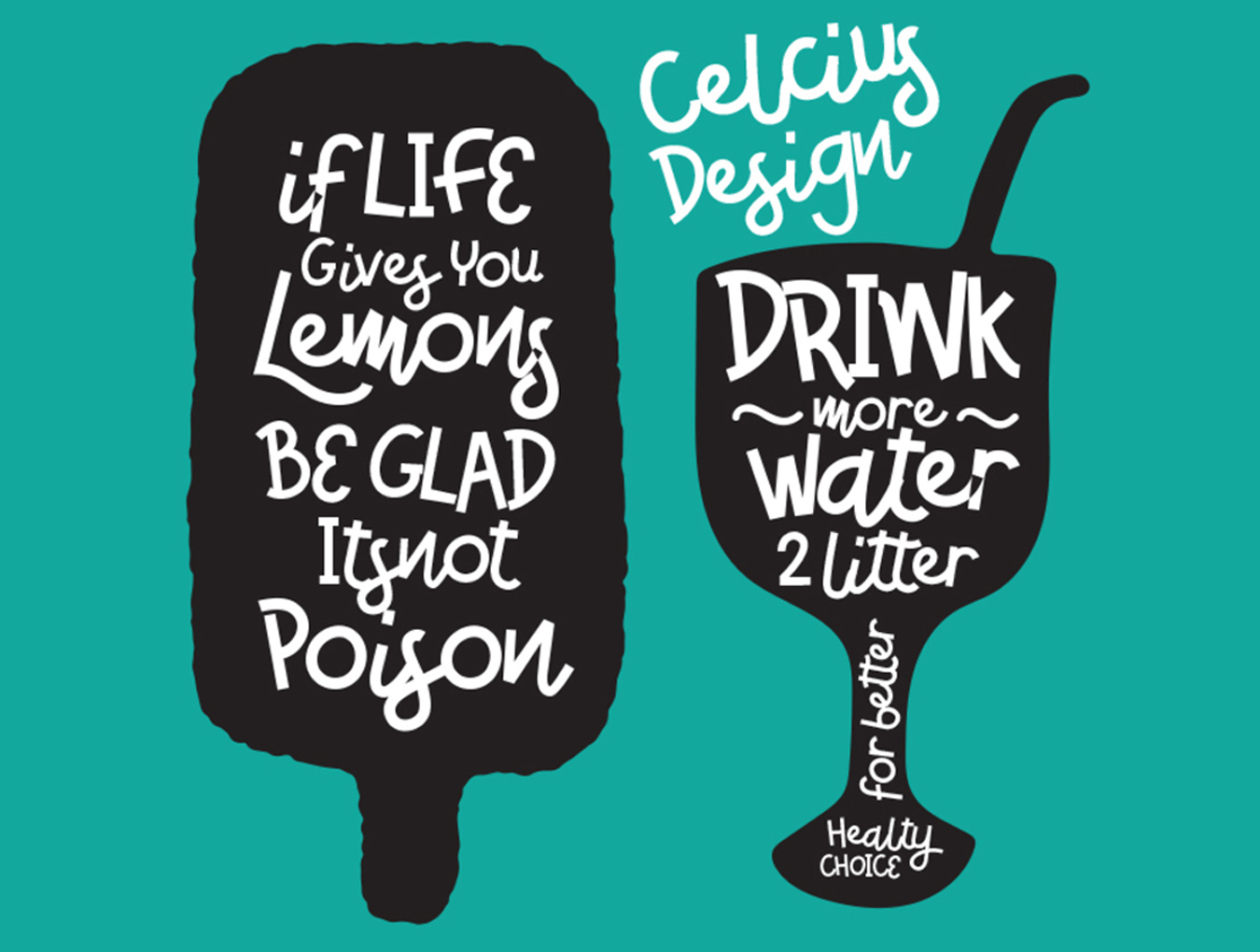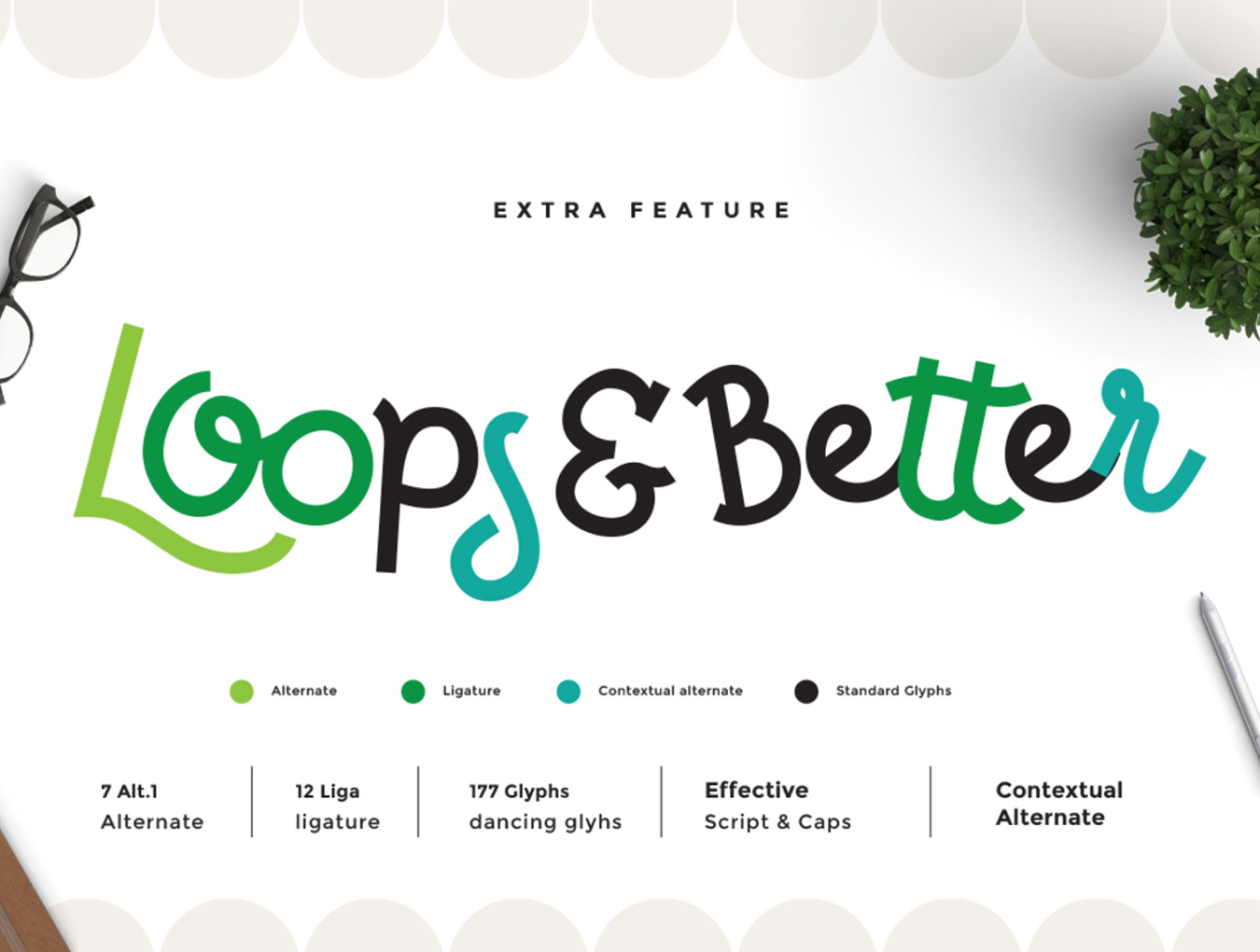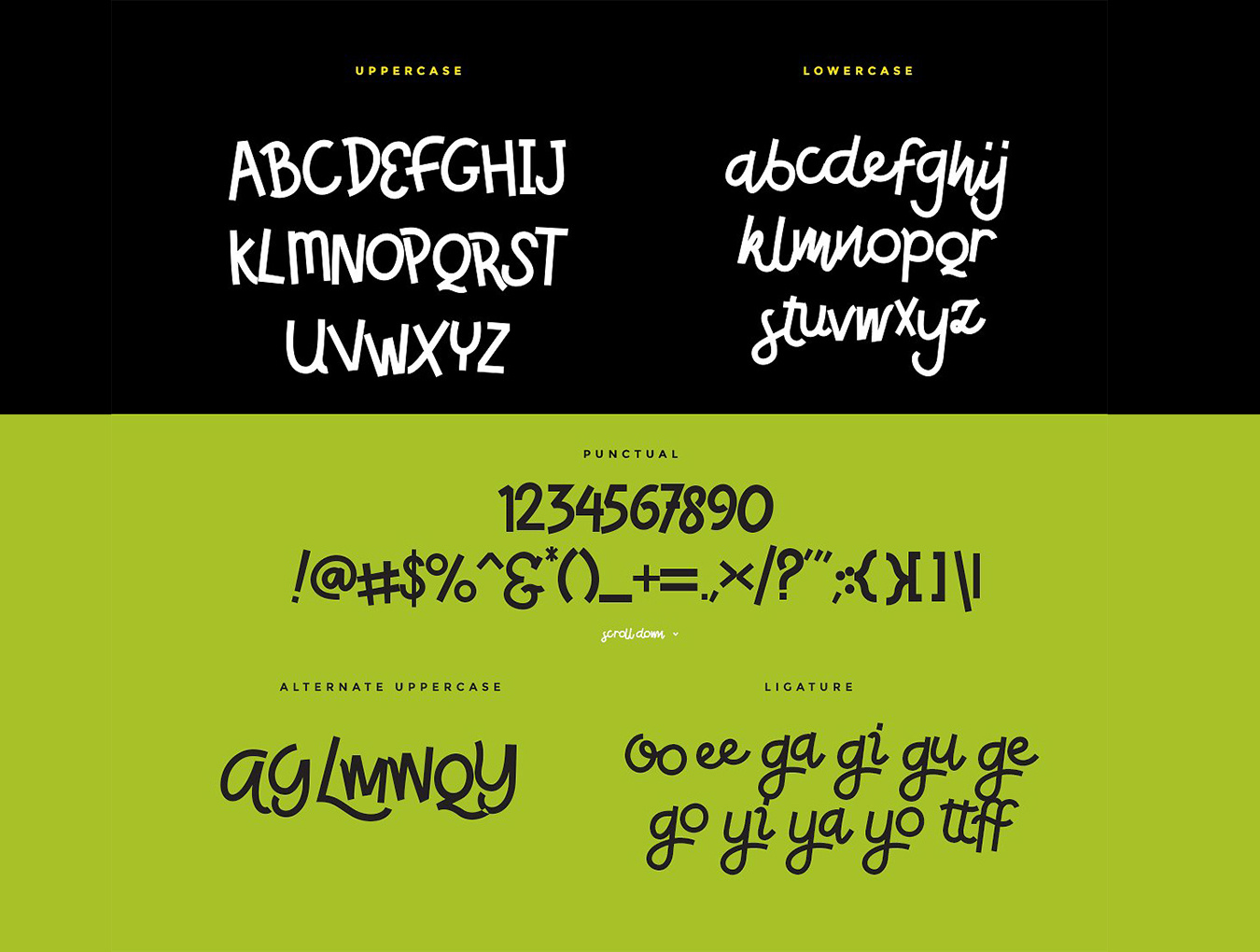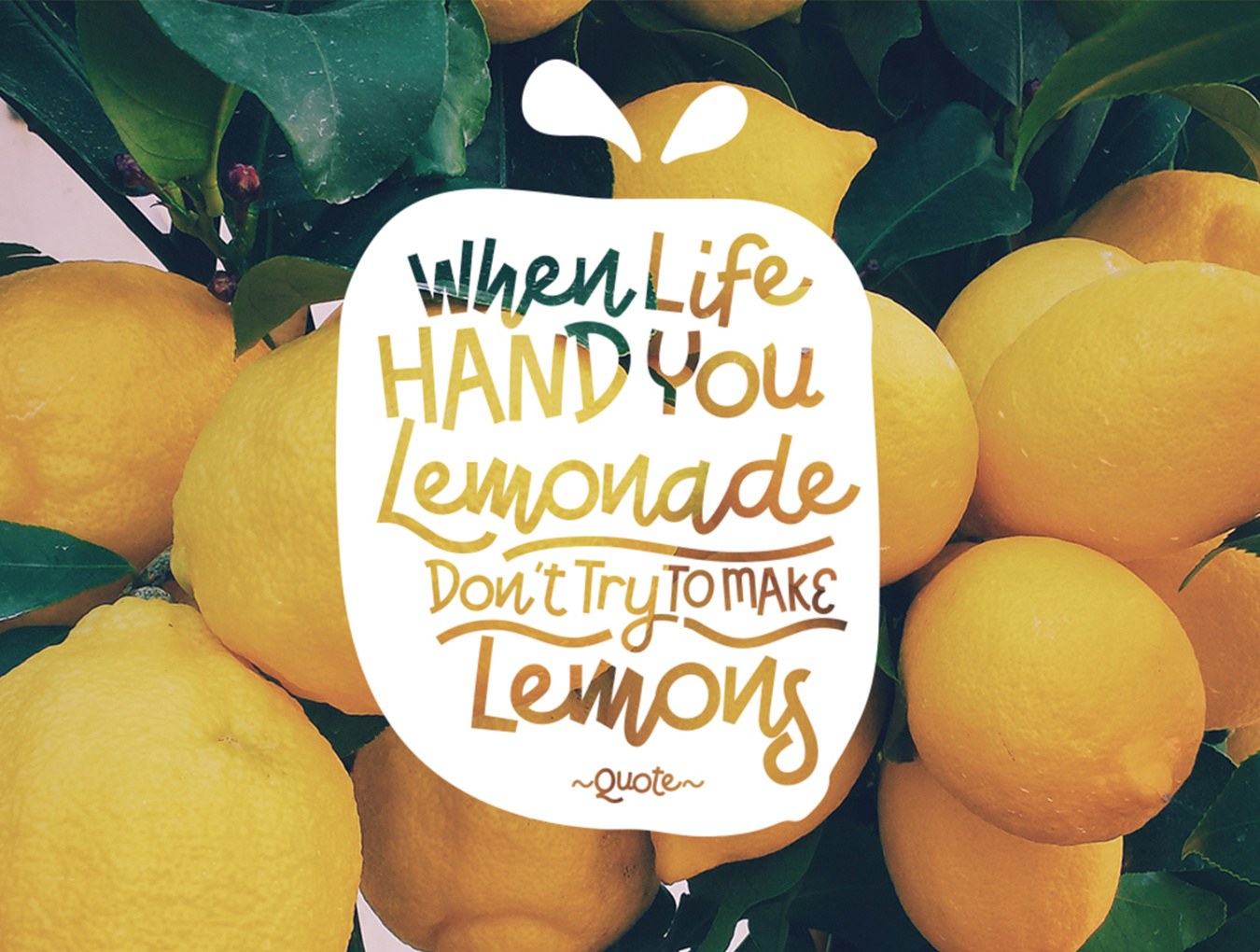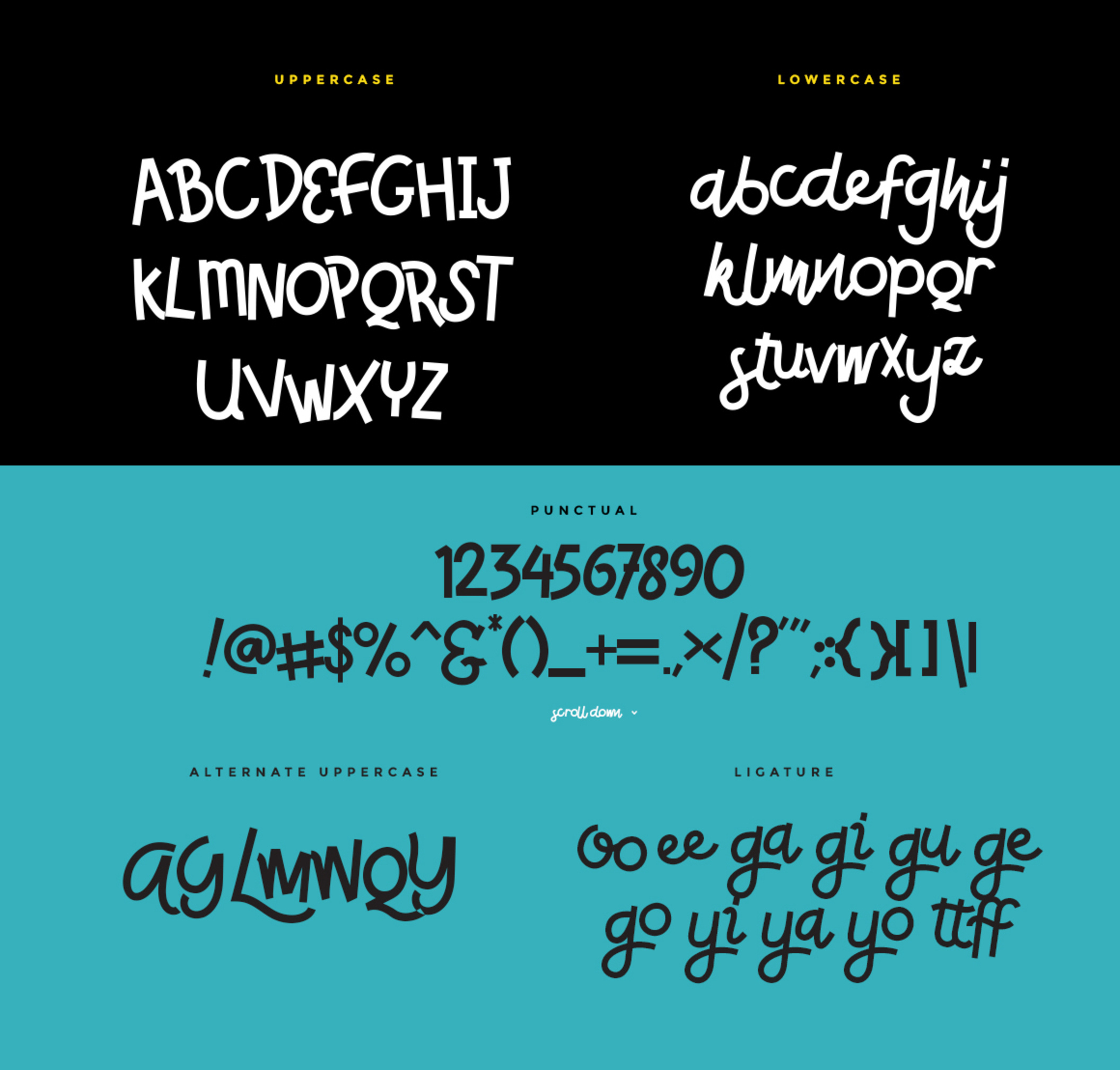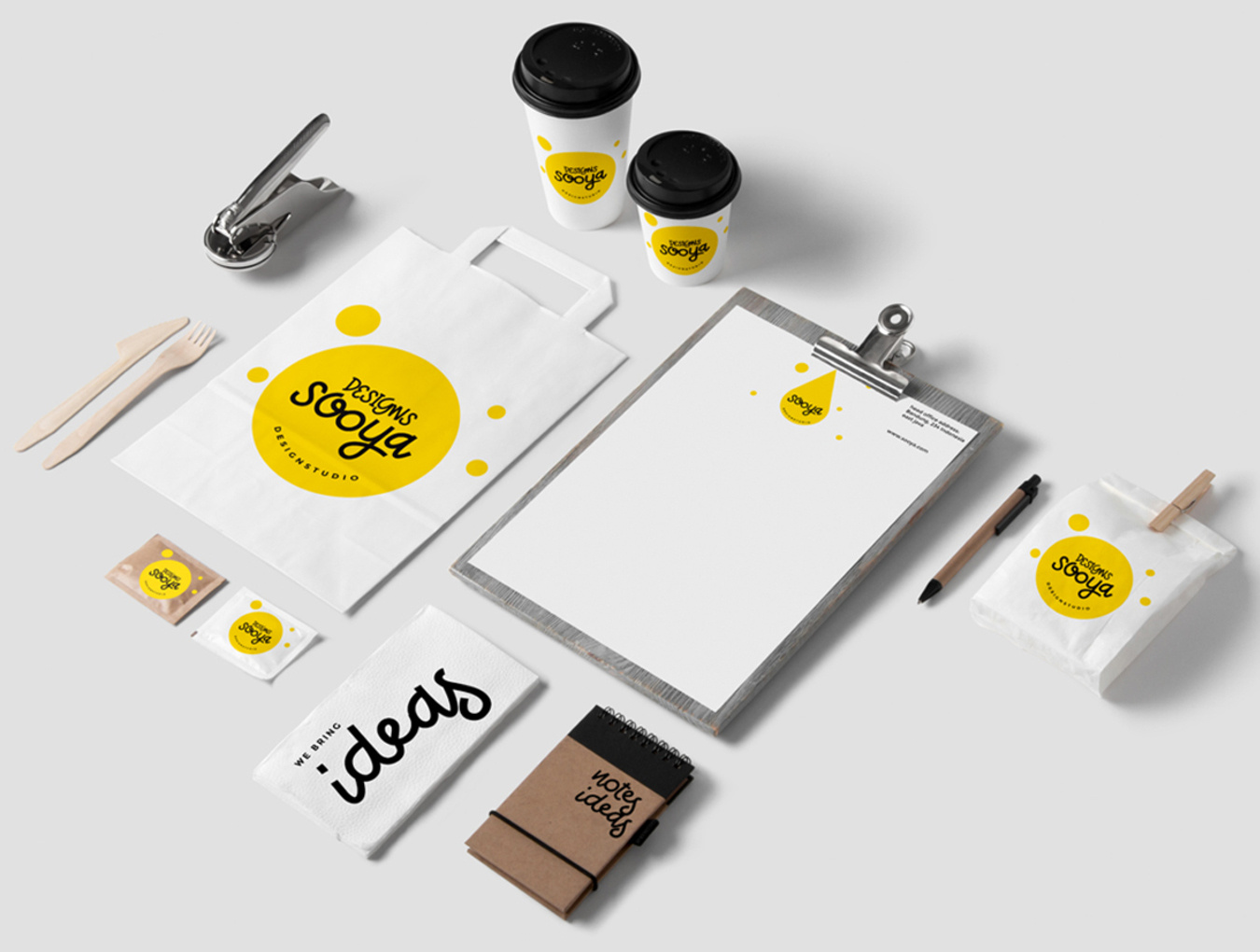
Sans Caps&Script组合字体,品红拿铁
品红拿铁是Sans&Script字体之间的半组合。这个非常有趣的概念非常微妙,对于简单的品牌推广,简单的引语,标识,食品促销标题,食品标识,菜单,海报,邀请卡或卡通电影片名都很完美。品红拿铁来与简单的功能来完成简单的类型/标志。 Opentype功能:Ligature - 上下文替代 - Alternate - Ss01 - Script&Caps